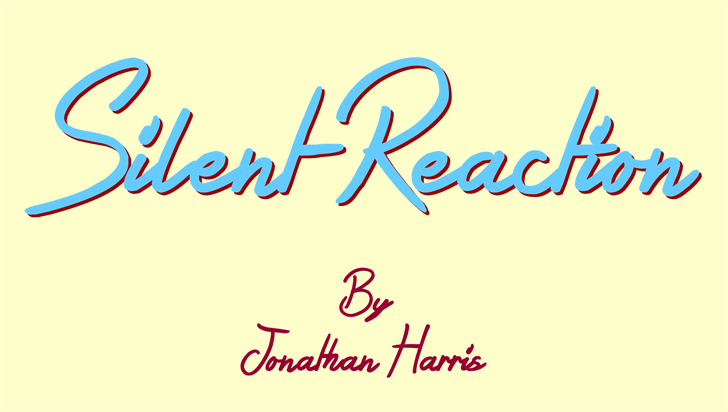
Silent Reaction font
A ‘Silent Reaction’ é uma fonte escrita a mão criada pelo designer Hamilton. Seu estilo suave e harmonioso proporciona um visual elegante e moderno, adequado para uso tanto nos arquivos de texto quanto nas criações gráficas digitais. Com seu design natural e fluido, esta fonte transmite confiança em qualquer projeto onde ela é usada. Perfeito para designers que buscam uma fonte a mão com um toque de minimalismo, a ‘Silent Reaction’ traz sua assinatura única ao seu trabalho. Ideal para criações de newsletter personalizadas ou aplicativos móveis, esta fonte vai dar um toque especial à sua marca. Nossa fonte é pura e suave em estilo, mas ainda possui o encanto único que só uma escrita a mão pode oferecer. Se você está procurando por uma fonte apropriada para projetos pessoais ou comerciais, com certeia que a ‘Silent Reaction’ será uma escolha ideal. Para informações sobre como usá-la comercialmente ou detalhes adicionais da fonte, visite o site http://www.tattoowoo.com ou entre em contato diretamente conosco no email .